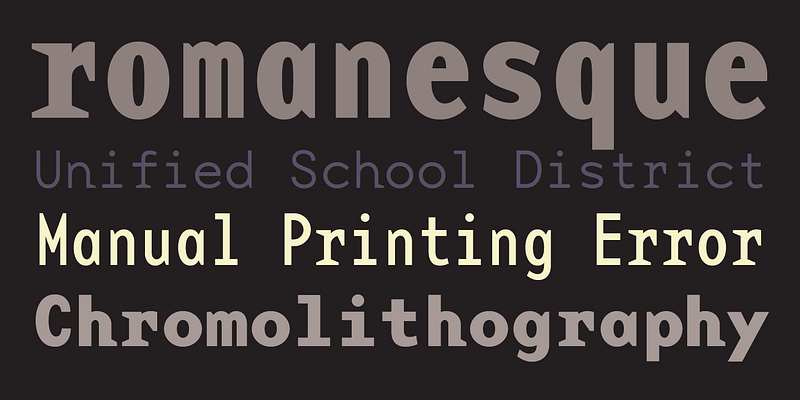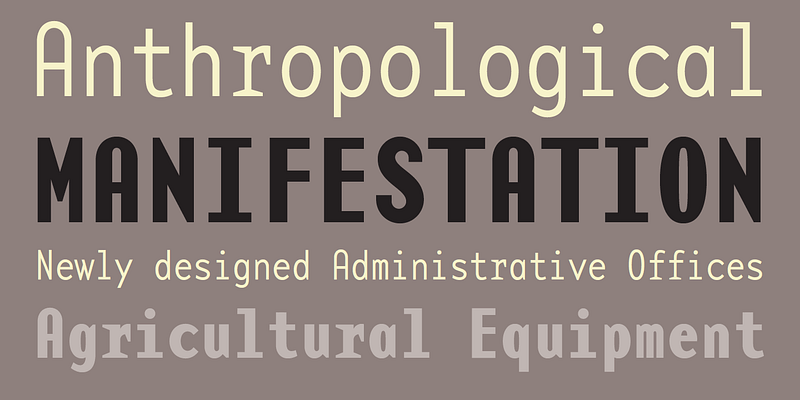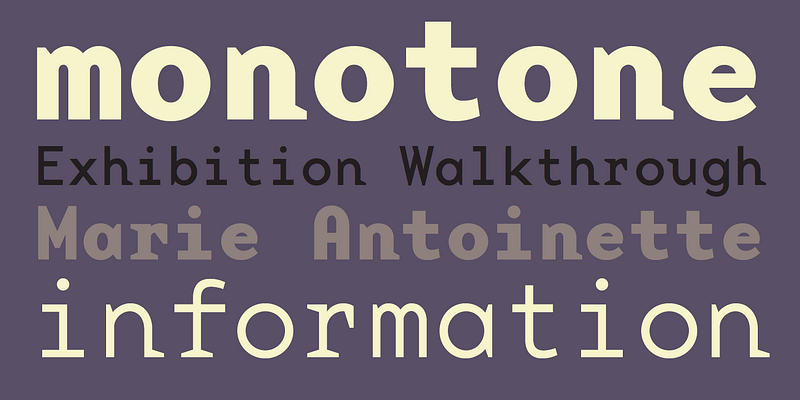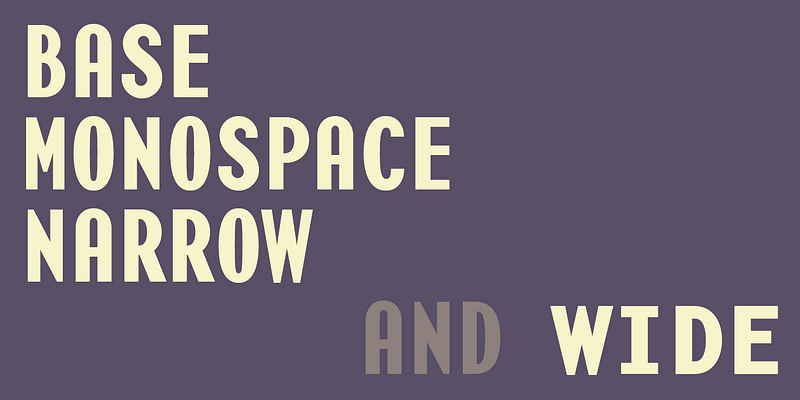
Base Monospace gehört, wie der Name schon sagt, zu einer Kategorie von Schriften, die sich durch Buchstabendesigns auszeichnen, die jeweils nur eine einzige Satzbreite einnehmen, wie die berüchtigte Schreibmaschinenschrift Courier (1956 von Howard Kettler entworfen) und die vielen anderen Monospaced-Schriften, die ihr Design inspirierten.